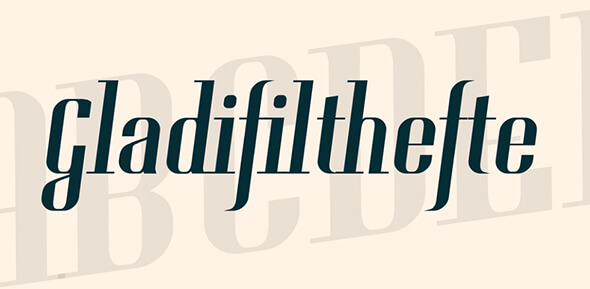
無料で使える!キャッチーな見出しのためのフォント 20選
人の目を引くキャッチーな見出しを作るためのフォントをお探しではないですか? この記事では20個もの素晴らしいデザインのフォントのセットを紹介します!書体は大事で特にタイトルはブログや記事で一番最初に目に触れられる場所なので注目されるタイトルを作りましょう!
見出しに合うフォントを見つけ出すのは大変かもしれませんが、これらの無料のフォントはあなたにぴったりです。目を引くデザインによって、あなたのコンテンツは絶対注目を浴びることでしょう。様々な特徴を持ったスタイルからこれといったものを選び出すことができます。
Monument Valley – Font
このフォントはモダンなイメージなのでどのようなプロジェクトにも使うことができます。この書体は見出しにぴったりで、注目されること間違いなしです。
Let That Be Enough – Tall Typeface
SkarpaLT – Font
AgaSilvaさんによって作られたこちらのフォントは個人的に使う場合は無料ですが、商業用となるとデザイナーに連絡しなければなりません。
GardenPartySans
この斬新なフォントはとても緻密なデザインでできています。大文字には花が象られ、とても目を引きます。
Deutschlander – Typeface
KG Ways to Say Goodbye – Font
Kimberly Gesweinさんによって作られたこちらの素敵なフォントは手書きのようなデザインで可愛らしく、個人目的であれば無料で使えるものです。
Caledo Font
こちらはBastien Sozooさんによって作られたフォントで、個人用にも商業用にも使えるものとなっています。
KG Rise UP by Kimberly Geswein – Font
これもまた斬新な書体で、見出しにぴったりです。手書きのようなデザインと丸い書体のフォントで個人目的のプロジェクトであれば、無料で使うことができます。
Gladifilthefte – Tall Font
大胆なこちらのフォントを見てみてください。どのようなニーズにも答えてくれる個人用かつ商業用に無料で使えるフォントです。
Little Rickey NF Font
DK Sleepy Time by David Kerkhoff – Font
こちらの可愛らしいデザインもフォントは見出しにぴったりのものです。個人用はもちろん無料で使え、商業用の場合はデザイナーに連絡しましょう。
November Sky Demo – Typeface
こちらの書体はRunes&Fontsによって作られたものです。個人用目的にしか使えませんが、無料です。
Tall Films – Font
こちらも簡素な書体のフォントで、個人用目的のみであれば、無料で使うことができます。
Men In Black Credits Font
斬新な書体で、創造的なこのフォントは大文字と小文字のコントラストによってとても目を引くものとなっています。
Bri – Wildflower Caps – Typeface
この目を引くフォントはSabrina Schleigerさんによって作られ、大文字のみのフォントですが、個人用目的では無料で使えます。
HomegirlHarvest Font
バラバラな書体が逆に目を引くこのフォントは是非とも今後のプロジェクトに最適でしょう。
Flamenco Typeface
個人用にも商業用にも使えることができる斬新なフォントとなっています。
InfraRed Typeface
Zdenek Gromnicaさんによって作られたこのフォントは、レギュラー、ブラック、ボールド、エクストラボールドの4つのスタイルから成り立っています。
Movies Tall Font
Edward Leachさんによって作られたこのフォントは、個人用プロジェクトであれば、無料で使うことができます。